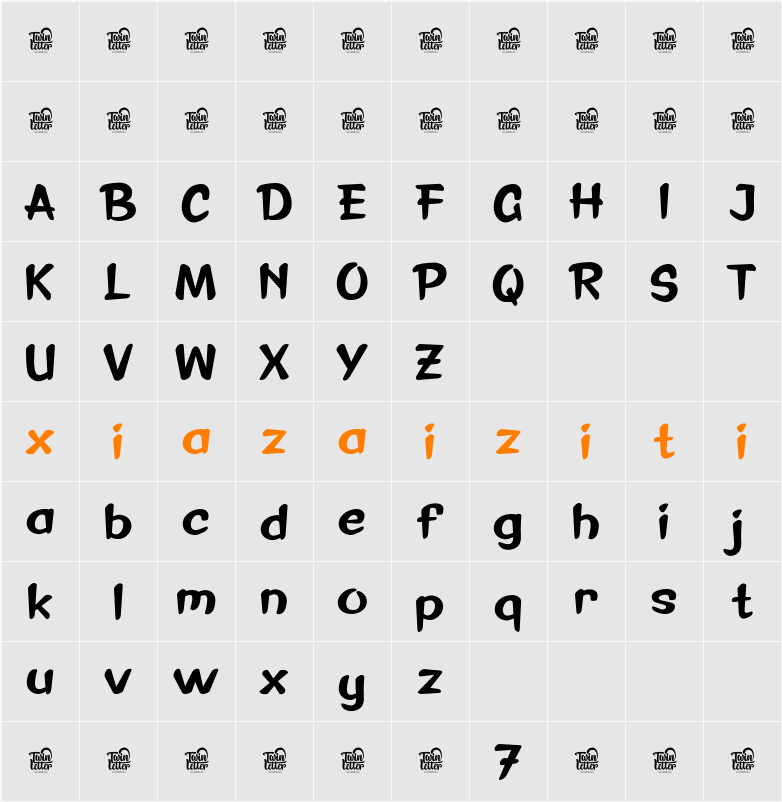
ZENLITH Trial
ZENLITH Trial,这款字体结构工整、笔画清晰,兼顾美观与易读性,适用于标题、正文、海报、包装、LOGO 等多种场景。字形优雅稳定,风格百搭耐看,适配日常排版与创意设计,让文字呈现更舒适、更具质感。ZENLITH Trial一笔一画,皆是细节,以均衡的比例、流畅的线条打造舒适视觉体验,字形端正大气,风格简约现代。无论是商业设计、品牌宣传还是日常排版,都能轻松驾驭,让文字更有格调与力量。ZENLITH Trial字体下载。